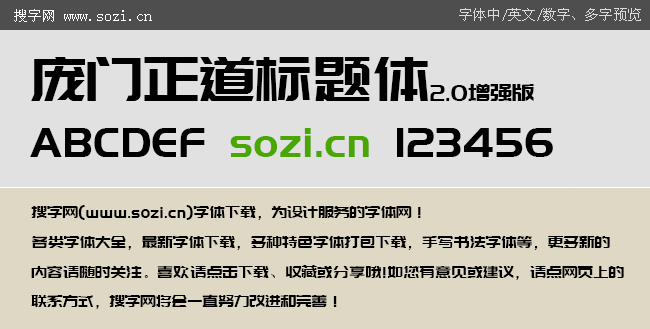
龐門正道標(biāo)題體2.0增強(qiáng)版
搜字網(wǎng)提供一款龐門正道標(biāo)題體2.0增強(qiáng)版中文字體下載,龐門正道標(biāo)題體是一款知名設(shè)計(jì)博主阿門推出據(jù)稱耗資超10W的字體,并且是永久免費(fèi)授權(quán)商用。整體字形筆畫均衡,風(fēng)格現(xiàn)代,字體方中帶圓,端莊雅致,簡(jiǎn)約時(shí)尚。本作品適用于胖體設(shè)計(jì)字體、標(biāo)題設(shè)計(jì)字體、品牌設(shè)計(jì)字體、動(dòng)漫設(shè)計(jì)字體等應(yīng)用。